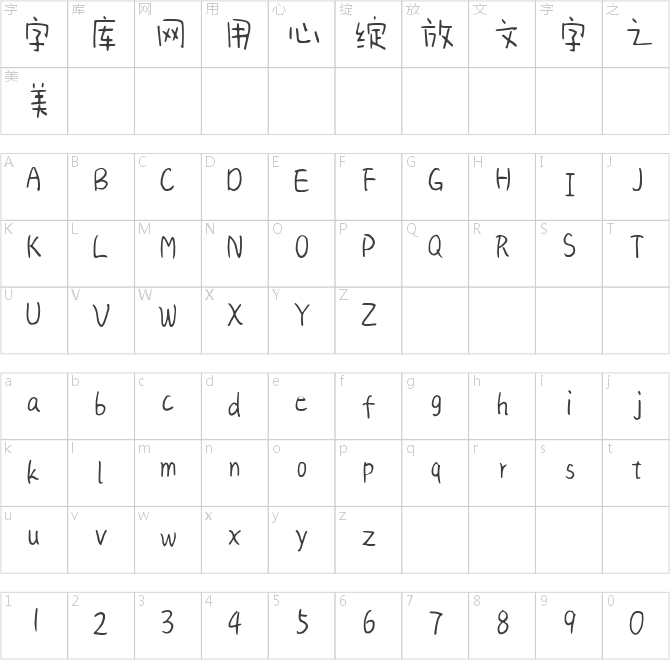
字體名稱:
字語(yǔ)萌動(dòng)體
字語(yǔ)萌動(dòng)體字體萌動(dòng)體字庫(kù)是一款讓人賞心悅目、百看不厭的中文字體,適合各類廣告和產(chǎn)品包裝設(shè)計(jì)應(yīng)用,字體大小8.69MB,格式為ttf字體,上傳用戶是素年錦時(shí),作者/版權(quán)方為字語(yǔ)坊